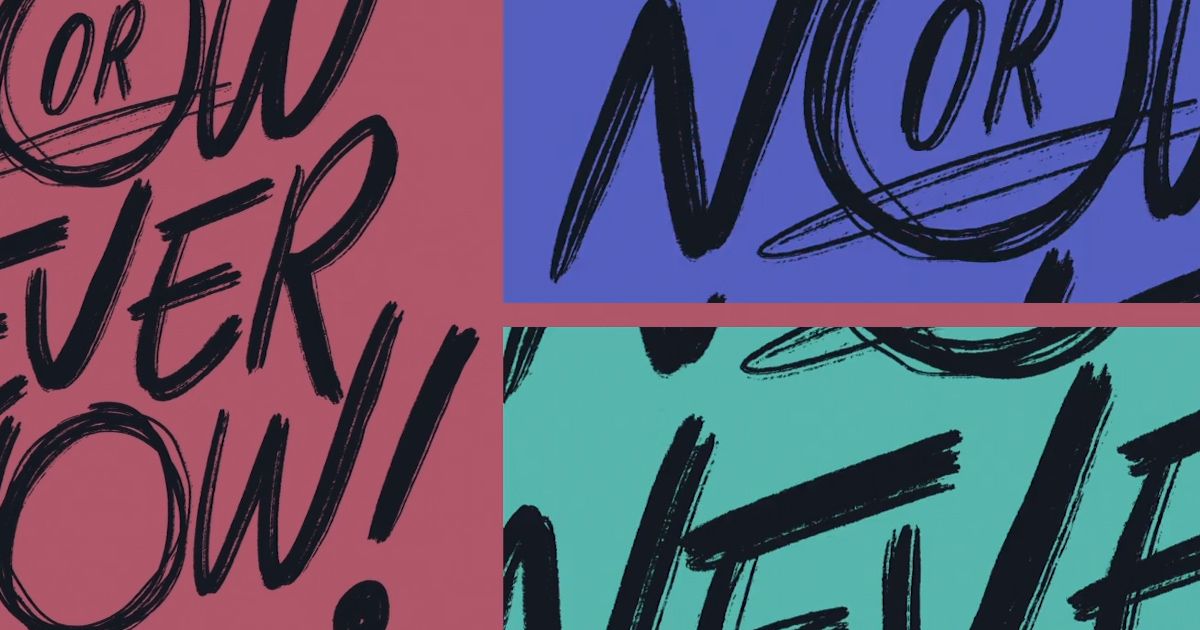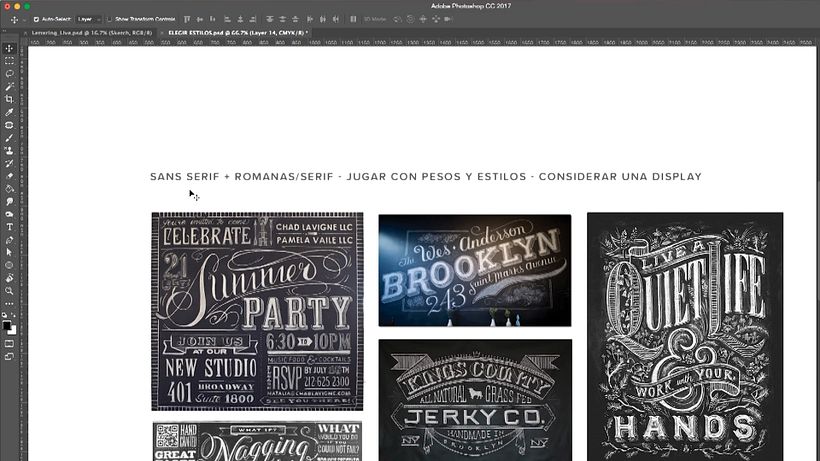
Tutorial Tipografía: cómo elegir tipografía para tus proyectos de ilustración
Sindy Ethel te da las claves para triunfar a la hora de elegir un estilo de letra
Cada estilo de letra es un mundo, y cada uno de estos mundos nos remite a un tipo de sensaciones completamente diferente. No es lo mismo utilizar una letra clásica con serifas que una sans serif moderna, igual que no es lo mismo trabajar con una script que con una display con motivos de fantasía. Entender qué significa cada uno de estos estilos y qué pueden comunicar es una habilidad esencial de cualquier creativo que trabaje con letras.
En el siguiente vídeo, la diseñadora e ilustradora Sindy Ethel (@sindy_r3do), que junto a Alan Rodríguez forma el dúo creativo R3DO, comparte contigo sus claves esenciales a la hora de elegir un estilo de letra para tus proyectos de lettering.
Busca inspiración en letras ya existentes
Es decir, trabaja con referencias. Dependiendo del tipo de proyecto al que te enfrentes (no es lo mismo un lettering para restaurante, por ejemplo, que para una guardería), tendrás que fijarte en distintos periodos históricos, diseñadores conocidos o estilos ya trabajados, y que remiten a sensibilidades o estéticas particulares. No tengas miedo de investigar, no solo en la red, sino también en archivos o bibliotecas.
Procura que la letra transmita lo que buscas
En ese sentido, no olvides que cada estilo de letra transmite una cosa completamente distinta. Las letras con serifa, por ejemplo, pueden remitir a un cierto clasicismo mientras que las sans serif, sin adornos, suelen estar vinculadas a una estética más moderna. Escoger una letra que no vaya en la línea de lo que quieres transmitir puede ser un grave error.
Define claramente con qué trabajarás
Una vez hayas revisado referentes y sepas exactamente lo que quieres transmitir, debes establecer con qué estilo o estilos de letra trabajarás. Solo partiendo de estos estilos podrás empezar a organizar tu composición tipográfica. Por ejemplo, puedes apuntarte que trabajarás principalmente con sans serif y quizá alguna letra romana, te centrarás en jugar con pesos y estilos y considerarás introducir una letra display (un tipo de letras con mucha personalidad, creadas para ser usadas en formato grande).
Aquí puedes apreciar distintos referentes de trabajo y unas coordenadas generales sobre el estilo